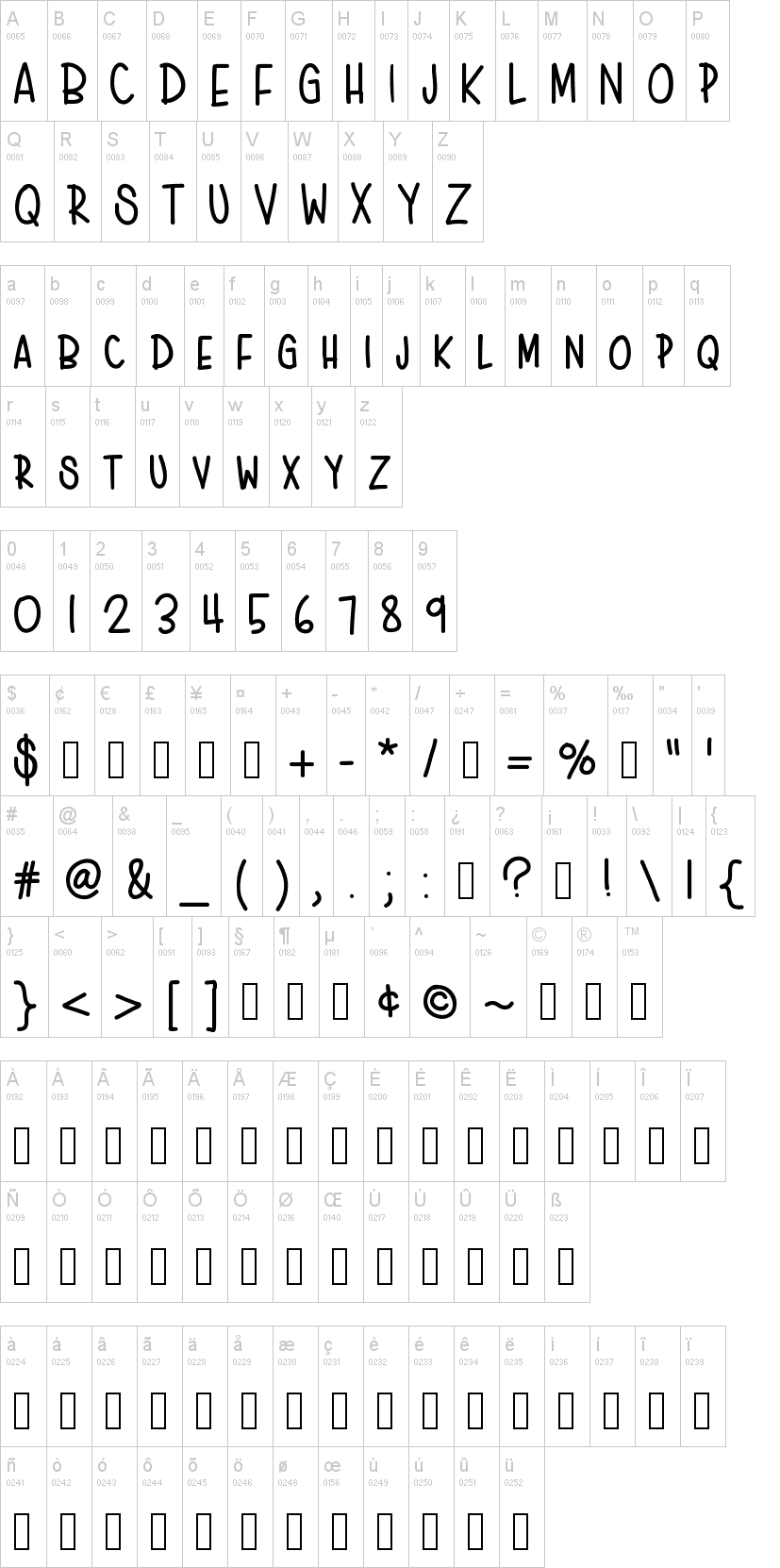
? Hello Cartoon 字体是一款带有活泼色彩的字体,它是一款简单易用的字体,可以帮助您在网页和其他场景中制作出活泼、有趣的文字效果。它适用于各种网页设计,拥有大量的字符,可以满足您的各种需求,并且具有良好的可读性。内容介绍
Hello Cartoon是一款非常不错的手写艺术字体,具有很好的视觉感,适合于文化类的宣传设计、商业类品牌的广告和产品包装设计以及个性化文字排版等较多场景。